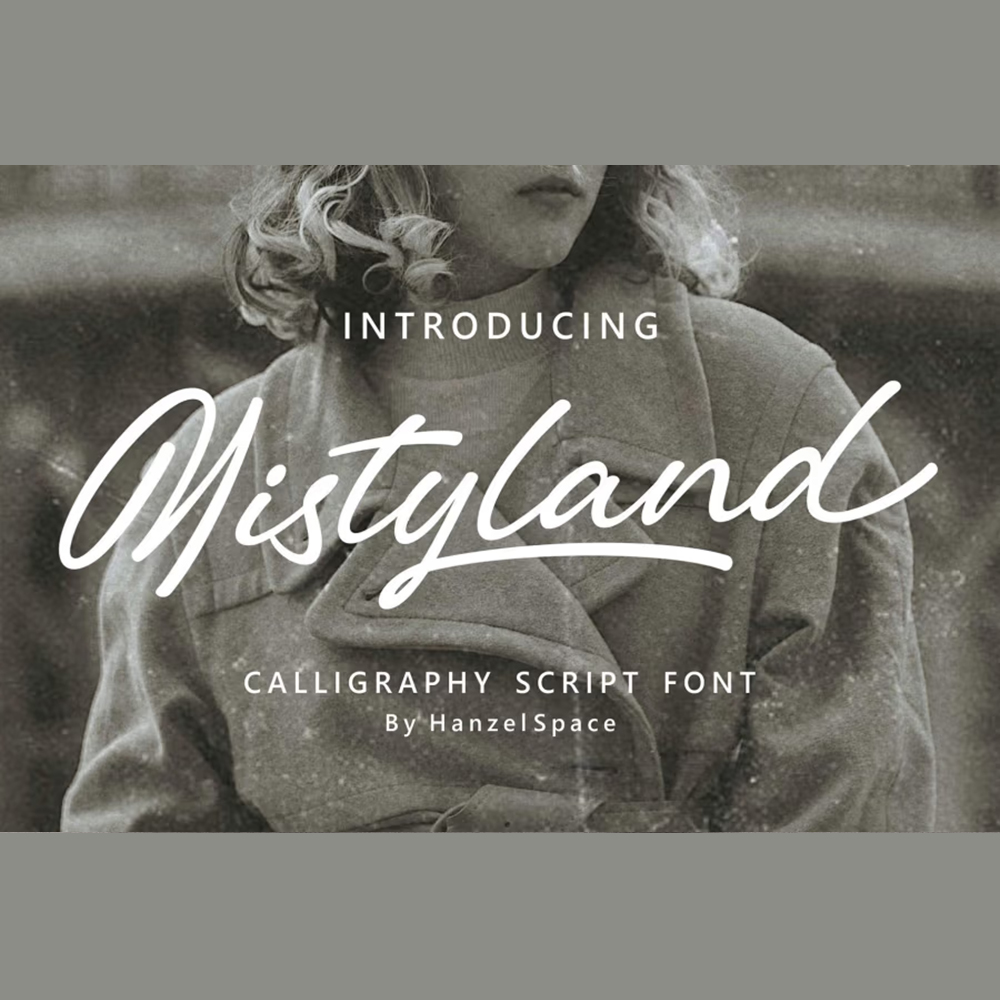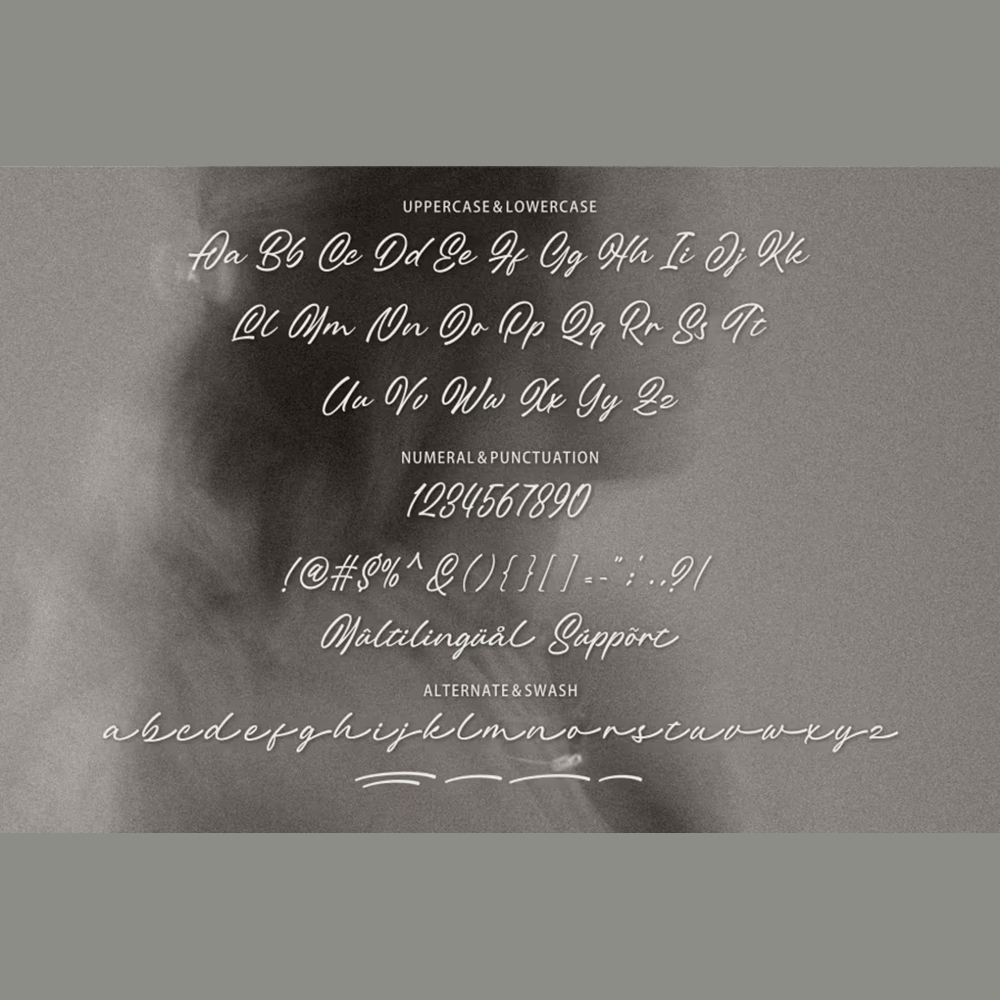
فونت پرمیوم و انگلیسی Mistyland Font از یک طراحی زیبا الهام گرفته شده است و آناتومی آن در هر منحنی متناسب و جذاب به نظر میرسد،…
فونت پرمیوم و انگلیسی Mistyland Font از یک طراحی زیبا الهام گرفته شده است و آناتومی آن در هر منحنی متناسب و جذاب به نظر میرسد، به طوری که این فونت برای استفاده در طرحهای مختلف برای برندسازی محصول، لوگوها، برچسبها و موارد دیگر بسیار مناسب است.
مزایای استفاده از فونت لاتین Mistyland چیست؟